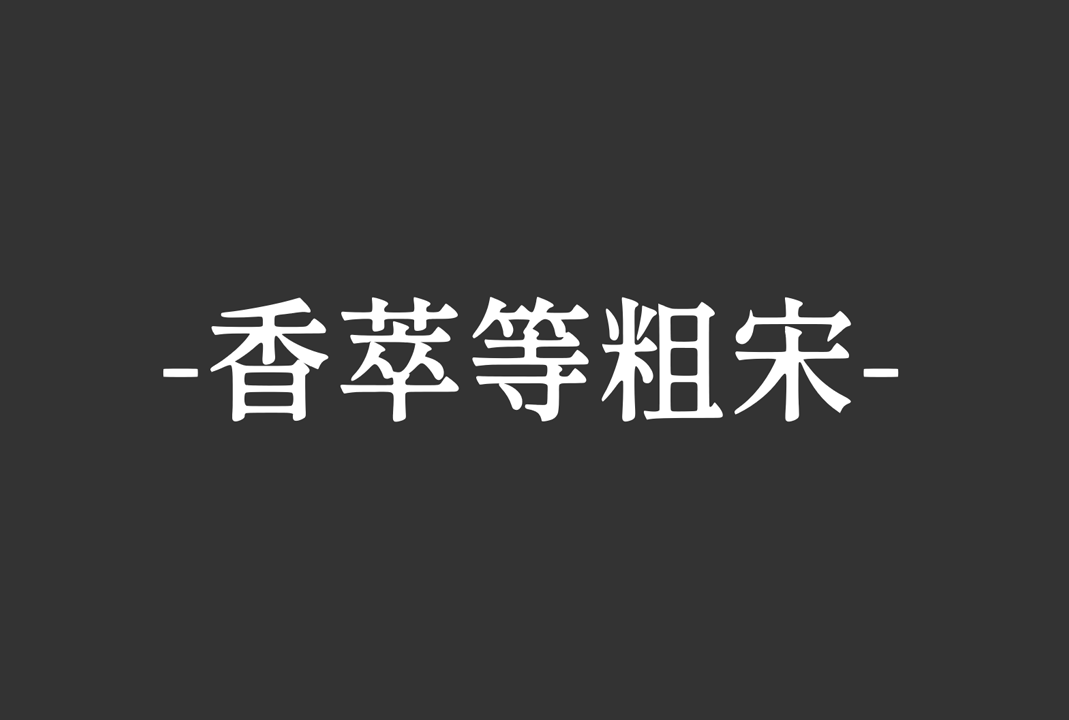
香萃等粗宋 ( XiangcuiDengcusong ) 设计富含人文气息,排版清朗温润,整个风格平静而温暖,字体在笔画起收与转角处平滑柔和,中宫略偏紧,兼具舒适感与严肃性。重新设定了横竖比例,并做了局部改良,可以在屏幕应用中有良好的表现,还适用于传统印刷媒介使用。
字体涵盖泛中日韩超20000字符,可放心使用。对于含有旧字形的汉字,除“浅残践劲茎径禅蝉惮箪莽蟒类器”等字使用中国大陆规范字形,其余使用旧字形。